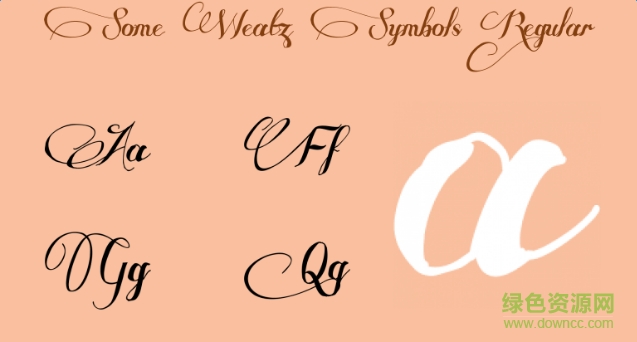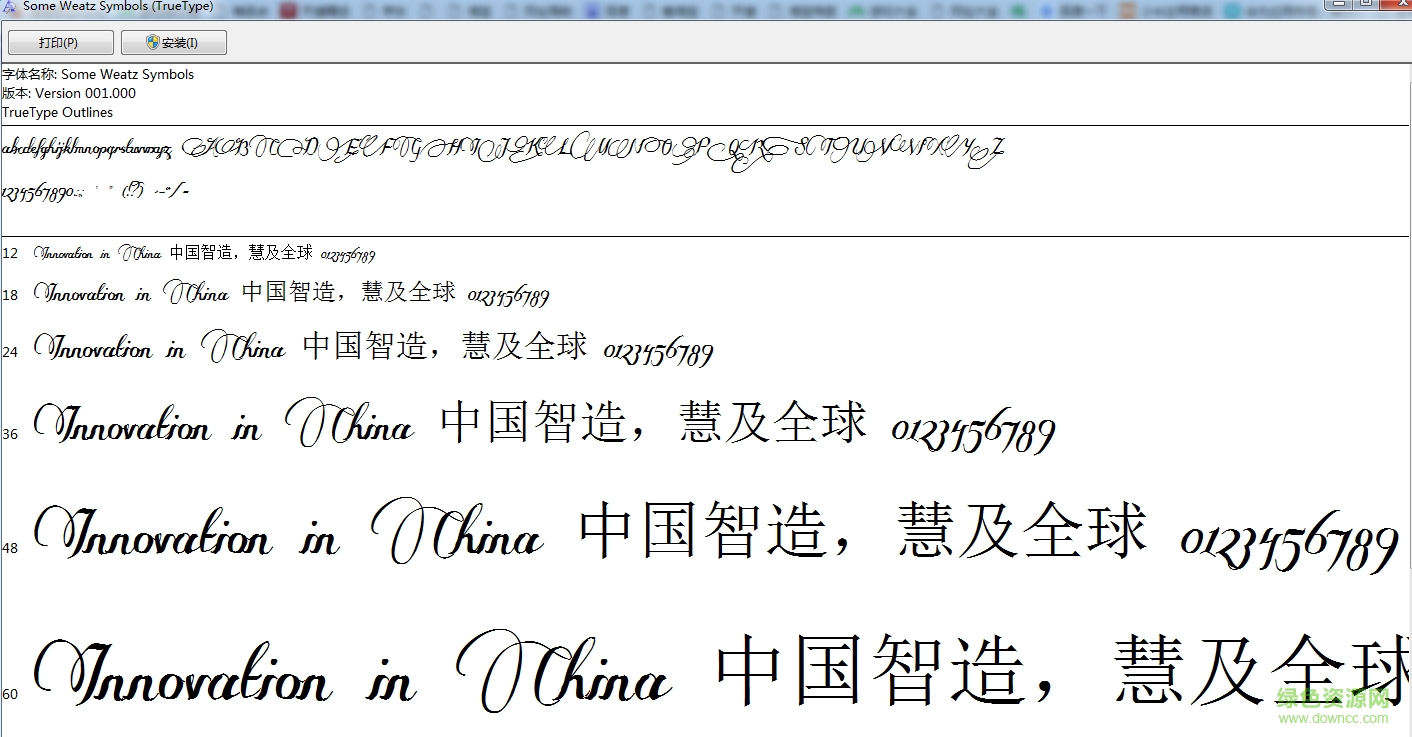
some weatz字體是一款裝飾性十分強(qiáng)的英文花體字體,制作精致,細(xì)粗變化得宜,有點(diǎn)像中文草書字體,需要這款字體的朋友趕緊下載收藏吧!
SomeWeatz字體常用于婚禮設(shè)計(jì)方面的字體,本作品也可用于廣告設(shè)計(jì)字體、網(wǎng)頁設(shè)計(jì)字體、包裝設(shè)計(jì)字體、 屏幕顯示字體等